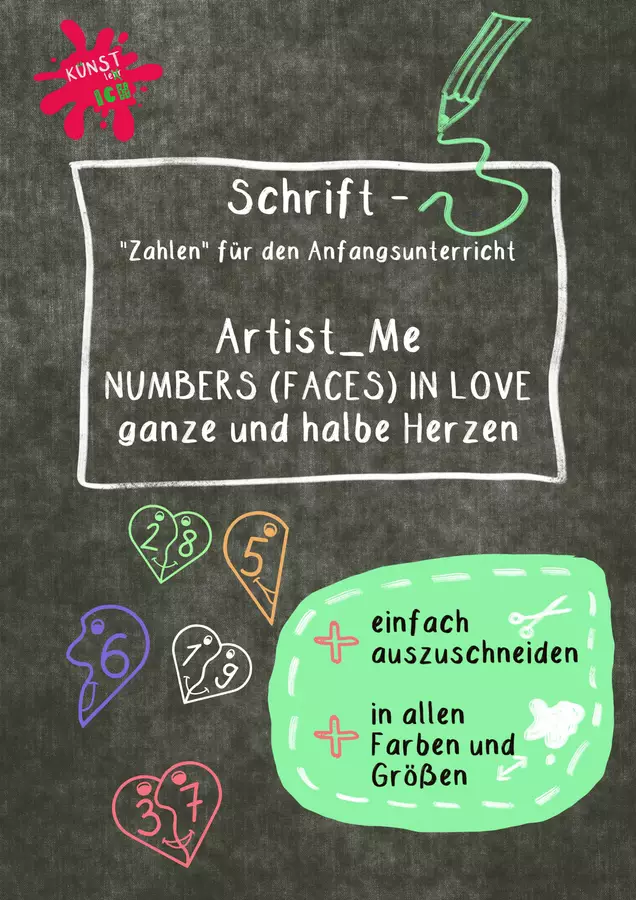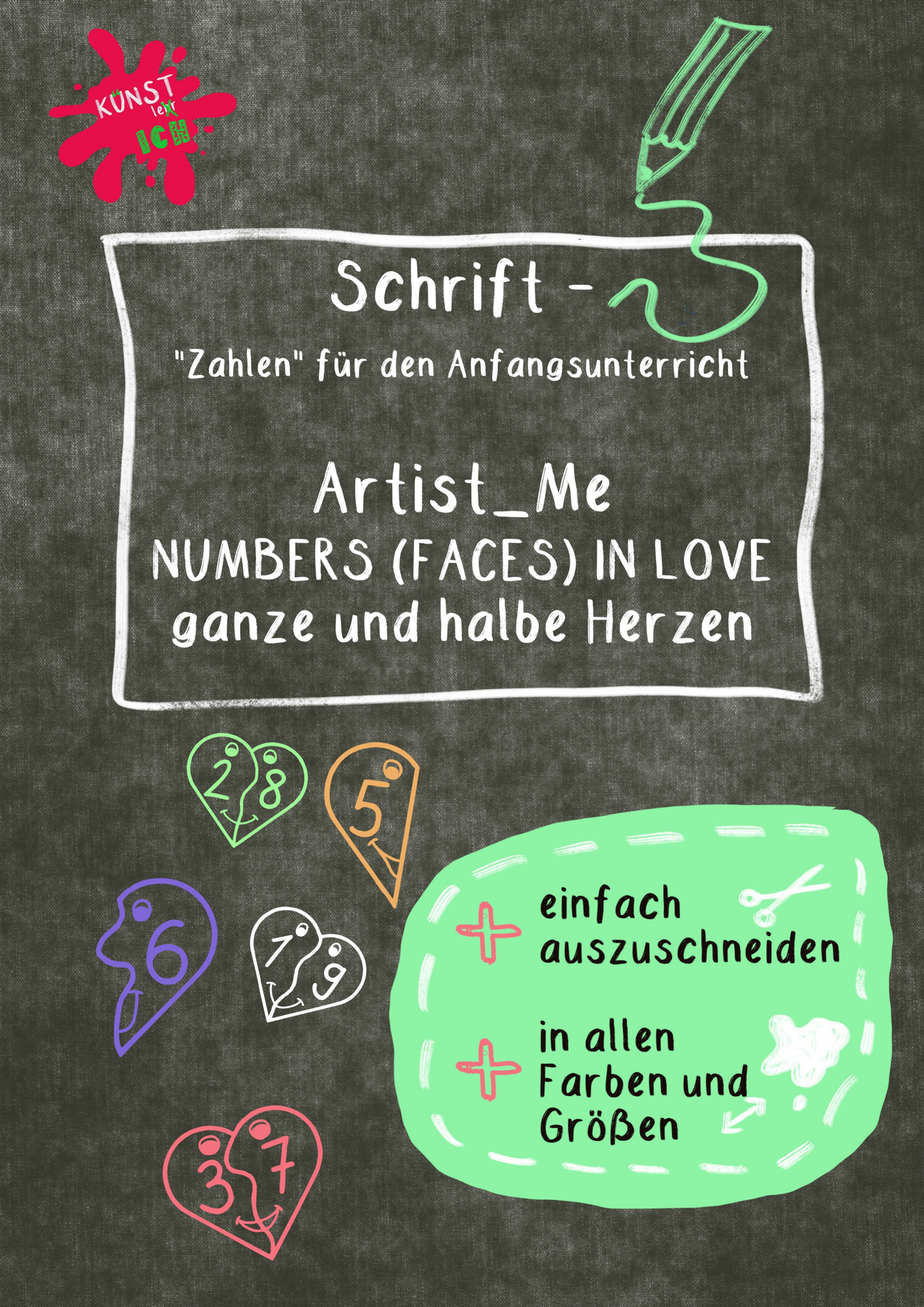
Poster - Schrift / Ziffern /Font - verliebte Zahlen - ❤ Artist Me - Numbers In Love (Faces) - ART.ist_ME // Kuenstler_Ich - Deckblatt
Mit dieser Schrift ist es ganz leicht individuelle Arbeitsblätter zu den verliebten Zahlen zu erstellen.
In dieser Variante liegen die Herzen mit Gesichtern, jedoch ohne Körper vor. Sie sind einfach von SchülerInnen auszuschneiden und zusammenzupuzzlen.
Schrift / Ziffern /Font - verliebte Zahlen - ❤ Artist Me - Numbers In Love (Faces)